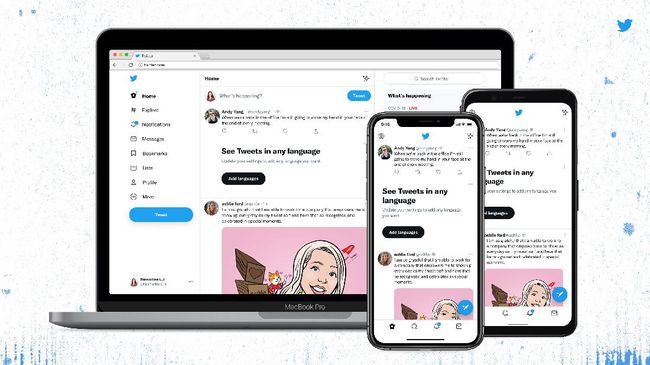
Desain dan Font Twitter Berubah, Netizen Kaget
Twitter baru saja merombak desain web-nya dan mengenalkan font baru bernama Chirp. Netizen langsung menyambut perubahan ini dengan kebingungan, bahkan ada yang protes font baru Twitter membuat mereka pusing.
Twitter mengatakan font Chirp buatannya sebenarnya sudah debut sejak bulan Januari. Sebelumnya, perusahaan berlogo burung ini selalu mengandalkan typeface seperti SF Pro, Roboto dan Helvetica Neue.
Saat debut di bulan Januari, font Chirp digunakan untuk kebutuhan promosi dan grafis, tapi belum dipakai sebagai font utama di aplikasi atau feed. Kini, Twitter menjadikan font Chirp sebagai font utama di web, mobile web, aplikasi Android dan iOS.
Selain itu, Twitter juga menjadikan teks cuitan yang ditulis dalam bahasa Barat menjadi rata kiri. Mereka mengatakan perubahan ini dibuat agar cuitan bisa lebih mudah dibaca sambil scrolling layar.
Perubahan paling besar terlihat di web Twitter.com. Warnanya kini dibuat lebih high-contrast begitu juga dengan tombolnya. Latar belakang abu-abu dan garis pemisah juga berkurang.
Salah satu perubahan terbesarnya adalah warna biru yang menjadi ciri khas Twitter justru berkurang. Misalnya, cuitan dan ikon navigasi kini berubah menjadi warna hitam saat menggunakan tema Twitter default dengan latar belakang putih.
"Kami memperbarui warna kami menjadi kontras tinggi dan warna biru jadi lebih sedikit -- perubahan yang dibuat untuk menarik perhatian ke foto dan video yang kalian buat dan bagikan," kata Twitter lewat akun @TwitterDesign, seperti dikutip dari TechCrunch, Kamis (12/8/2021).
Twitter juga berjanji akan meluncurkan warna baru dalam waktu dekat, tapi tidak diketahui dengan pasti apa maksud mereka. Saat ini pengguna yang sudah berlangganan Twitter Blue bisa mengubah warna dan ikon aplikasi, tapi layanan itu baru tersedia untuk iOS di Kanada dan Australia saat ini.
Netizen yang sudah melihat tampilan baru Twitter pun langsung ramai membahas perubahan desain ini. Saking ramainya, kata kunci 'Font' sampai trending di Twitter hingga Kamis (12/8) sore dengan lebih dari 441 ribu cuitan.
Sebagian pengguna ada yang kaget melihat tampilan baru Twitter, ada juga yang merasa aneh melihat beberapa huruf yang digunakan. Bahkan ada juga yang mengeluh sakit kepala dan kesulitan membaca font baru Twitter.
"font baru r nya gemoi," kata pengguna Twitter @evoctvesungchan.
"Ini font twitter ganti ya jd berasa mbulat mbulat kayanya g nya dulu gag gini gag sig," ujar netizen @depressionceri.
"Mata aku udah minus ditambah font twitter makin kecil, makin sakit aku bacanya😭😭😭," kata @bybluewind.
"Ubah font twitter bisa gak si🥲 greget bgt huruf g nya kek uget2," ujar @ejaeaj.
Kalian juga sudah melihat font dan tampilan baru Twitter detikers? Apakah membuat Twitter jadi terlihat lebih segar atau justru bikin mata pusing saat membaca?